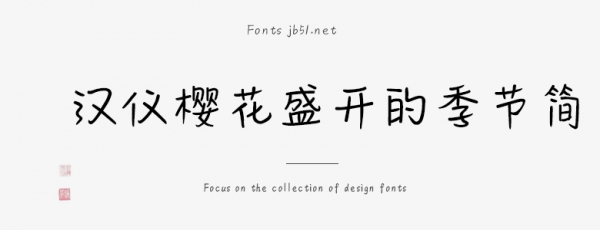
漢儀櫻花盛開的季節(jié)簡(jiǎn)是由漢儀字庫(kù)出品,字體筆觸適中,字形圓潤(rùn),具有很好的視覺感,適合應(yīng)用于藝術(shù)設(shè)計(jì)、平面宣傳設(shè)計(jì)、網(wǎng)頁(yè)設(shè)計(jì),書法字帖等領(lǐng)域,需要的朋友可以前來本站下載。